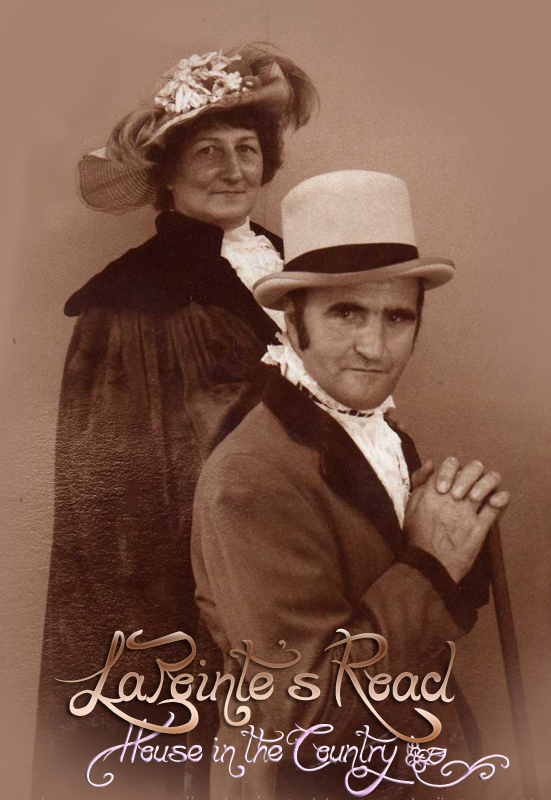
LaPointe's Road
LaPointe's Road di Albertine Nerevan è un font calligrafico gratuito caratterizzato da tratti ampi e fluidi, pronunciati cambiamenti di spessore e un movimento in avanti sicuro. Ampi fregi avvolgono le lettere tonde e le vivaci legature.
Il suo carattere di scrittura formale la rende perfetta per partecipazioni di nozze, branding per boutique e packaging di cosmetici, dove il lettering può diventare parte dell'ornamento. Si adatta inoltre a copertine di libri e poster di eventi incentrati su romance, moda o dramma storico, con un titolo manoscritto espressivo e un tratto marcadamente teatrale.